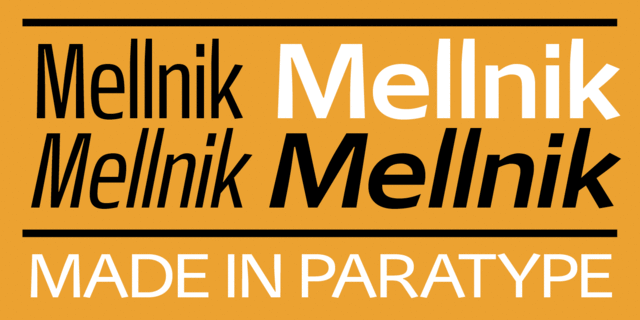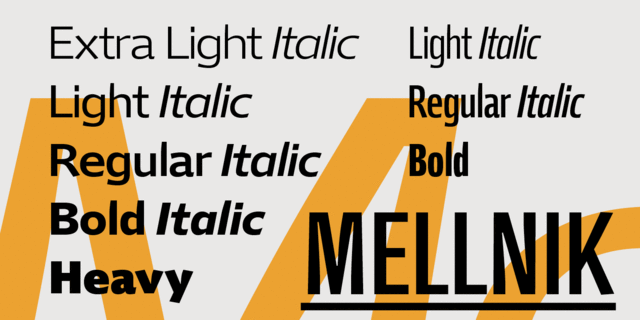
Mellnik (14 шрифтів)
Гарнитура Мельник в духе гуманистического гротеска разработана Олегом Карпинским для компании ПараТайп в 2006 году, состоит из девяти начертаний и содержит некоторое количество альтернативных знаков. Мельником можно набирать как большие текстовые блоки в рекламных буклетах, каталогах, журналах, так и выделительные слова и фразы. Возможно использование в качестве корпоративного шрифта. Пять узких начертаний добавлены автором в 2007 году.
Асоціації з сімейством шрифтів MellnikОсобистість і характер гарнітури:
делікатний, чистий, легкий, прохолодний, свіжий, модний, стійкий, серйозний, твердий, надійний, урбаністичний, мужній, сильний, важкий, помітний, яскравий, активний, стрункий, високий, рівний, Простий, важливий, гучний, мотивуючий, амбітний